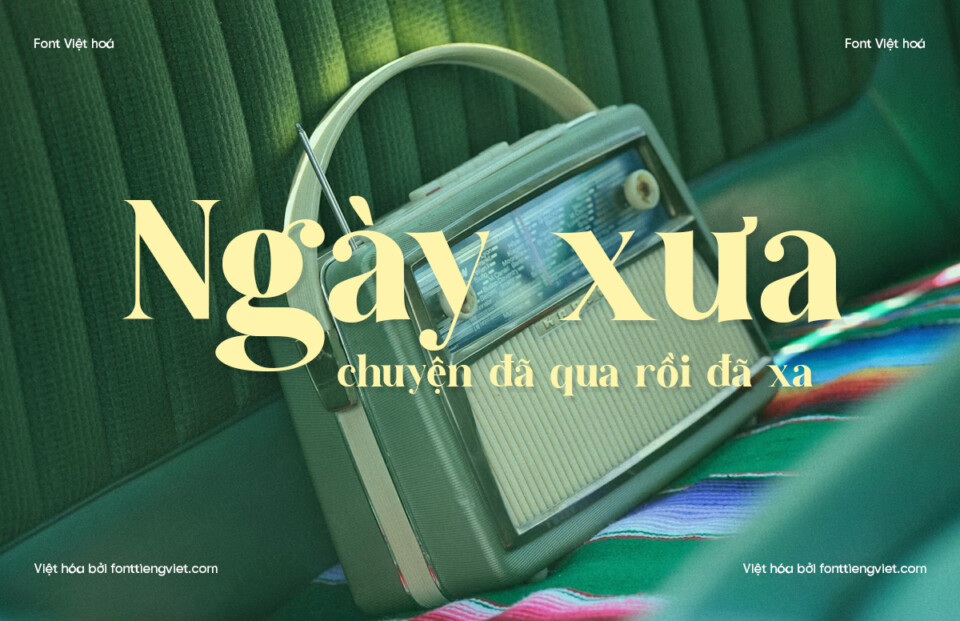
Tên font: Font Việt hóa VIP Moving
Tác giả: Graphicxell
Bạn đang tìm kiếm một font chữ có chân (serif) toát lên vẻ tinh tế, cổ điển nhưng vẫn giữ được sự sang trọng hiện đại? VIP Moving Việt hóa là lựa chọn tuyệt vời, mang đến một phong thái quý phái và đẳng cấp cho mọi ấn phẩm.
VIP Moving Việt hóa được thiết kế với các nét chân duyên dáng và tỷ lệ cân đối, tạo nên một vẻ đẹp hài hòa, lý tưởng cho: